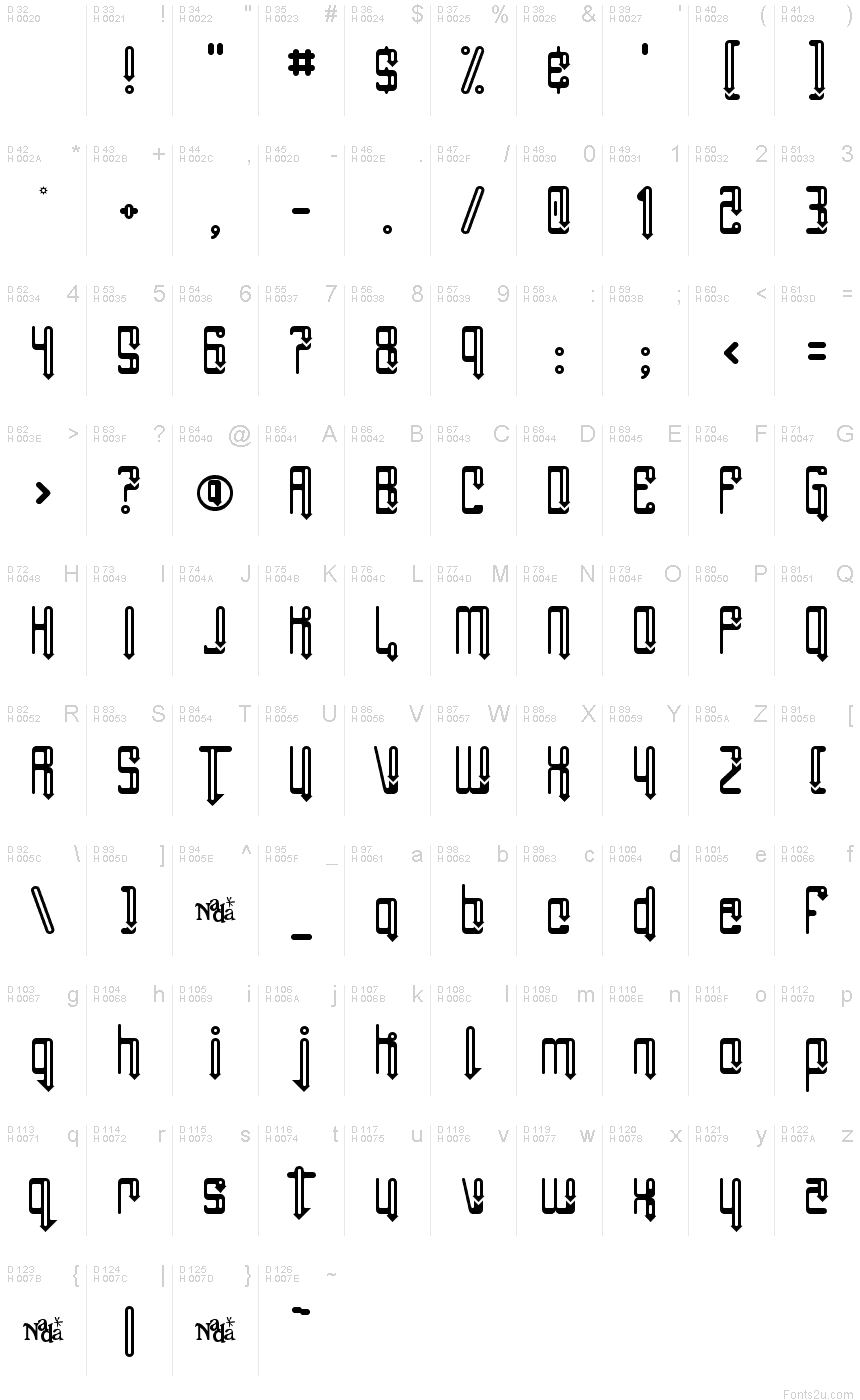
Angie Groovin di R.Gast - GreyWolf WebWorks è un font display gratuito, retro e groovy che trasforma ogni parola in un piccolo cartello stradale. Le lettere, alte e tubolari, poggiano su basi a forma di freccia, rendendo le righe di testo simili a una fila di indicatori audaci. I tratti sono spessi e arrotondati, con una lucentezza liscia, quasi plastica, che sembra uscita direttamente da una sala giochi vintage o da una pila di poster degli anni '70.
Angie Groovin brilla su locandine di concerti psichedelici, volantini per feste retro, loghi stravaganti, grafiche per i social, adesivi e design per merchandising. Il suo ritmo serrato e le verticali costanti creano una solida spina dorsale visiva, ottima quando vuoi che i titoli guidino lo sguardo attraverso il layout. Usalo in dimensioni grandi per il massimo impatto, quindi abbinalo a un carattere sans serif geometrico pulito della famiglia Angie o a un altro sans serif semplice per il testo principale, così da lasciare che le frecce funky siano protagoniste.